デザイン初心者は制作する際に文字や書体の基本的な特徴をまず覚えることが大切です。
書体は世の中にとても多くの種類があり、それを1つ1つ覚えるのは容易ではありません。この記事ではデザイン初心者が押さえておくべき書体のカテゴリや分類についてわかりやすく説明しています。
この特徴がわかればデザインに使用する書体選びにも困らなくなることだと思います。
デザイン初心者でも人を惹き付ける文字や書体の基本ポイントとは!?
読み手がデザインされた制作物や資料から受けるイメージは、デザインで使用された写真や画像だけではなく、書体の種類や文字要素の配置等により大きく変わります。
制作時にレイアウトされた文字の読みやすさや視認性も大切な要素の1つです。この記事では文字と書体の基本知識とその知識をデザインに取り入れる具体的な方法を説明します。
文字は情報伝達の基本要素になります。文字と書体は基本的に視認性を確保できているかどうかがポイントとなります。ですので読み手が制作物や資料から受けるイメージは、使用する書体がどのように使われているかにより大きく変わります。
読み手に伝えたい情報や与えたいイメージに応じて最適な書体を選択を選択して視認性を確保しておくことが必要です。
書体の種類は何があるのか?
和文にはゴシックと明朝体、欧文にはサンセリフ体とセリフ体があります。
ここでの和文は漢字、ひらがな、カタカナを扱うことが出来る書体の総称として記載しています。ここでの欧文はアルファベットや半角記号などの和文を取り扱うことができない書体の総称として記載しています。
和文書体の一例
欧文書体の一例
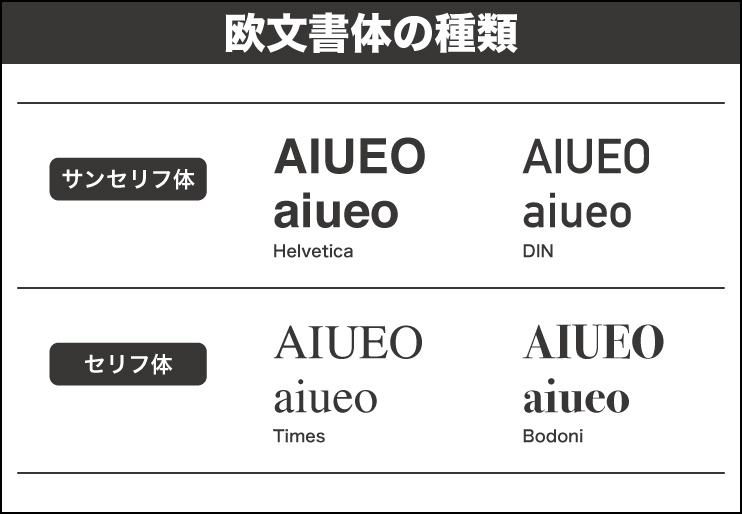
同じ文字でも書体により特徴が異なり見た目のデザインが変わります。大きな分類であるゴシック体と明朝体、サンセリフ体とセリフ体の違いを覚えておくと良いでしょう。
書体が与える文字のイメージとは何か?
デザインが読み手に与えるイメージは、どの種類の書体を使用するかによって大きく変わります。実際に下図2つのデザインを見てみましょう。
左側ではゴシック体とサンセリフ体を使用しています。右側では明朝体とセリフ体を使用しています。デザインレイアウトは同じですが、左側からはポップな感じのイメージを感じます。右側からは少し高級感のあるイメージを感じると思います。
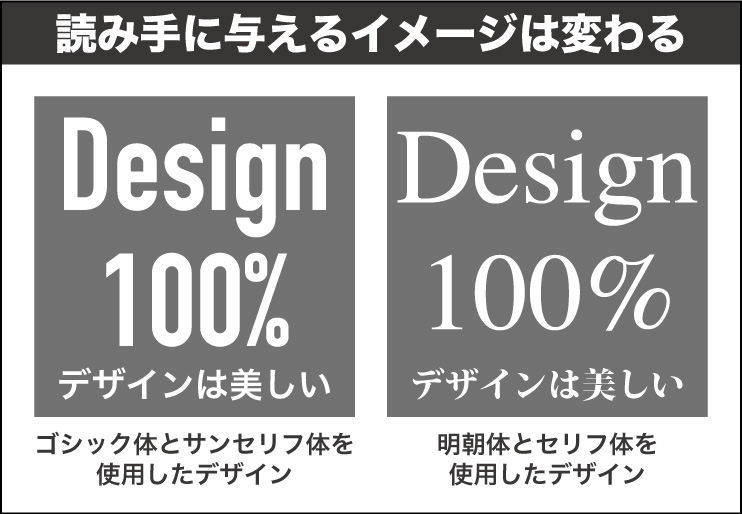
同じデザインレイアウトを使用していても、書体が書体が異なると見た目のイメージが異なります。書体はそれだけデザインのイメージを左右してしまうのです。
文字を書体の持つ力でデザインやレイアウトに生かしていこう!
下図にいくつかの具体的な制作を行ってみました。それぞれを見ると瞬時にイメージが異なることに気がつくと思います。
これは書体本来がもっている力ということです。デザイン初心者は同じデザインであっても基本となる書体を変更して2種類制作を行い、それぞれを見比べるとより効果がわかることだと思います。
自分なりのデザインの概念があるとは思いますが、ここではあえて固定概念を置いて試すと良いでしょう。きっと文字と書体のデザインヒントになることだと感じます。また、自分で何度も試すことで書体の基本知識は自然と身につくことでしょう。
左側はゴシック体を使用し、右側は明朝体を使用しています。
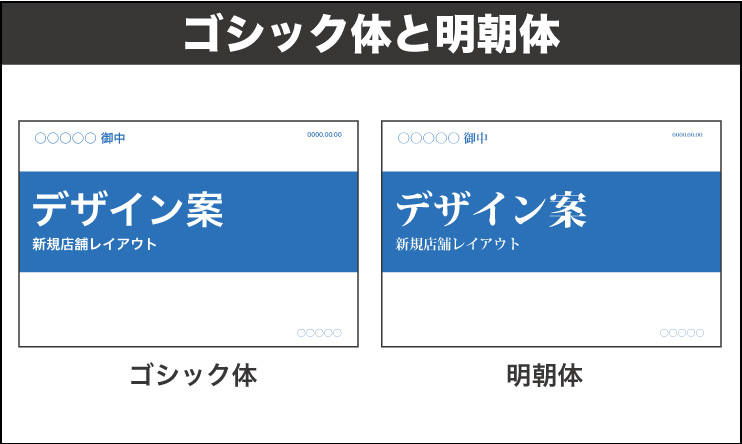
左側はゴシック体を使用することで文字の線幅がほぼ均一であるため視認性が高く、安定感のあるイメージになります。
右側は明朝体を使用することで文字の線幅に強弱があるため左側ゴシック体と比べ、タイトル文字が若干弱く見えますが、厳格・堅い・美しいといったイメージがあります。
下図の左側はサンセリフ体をメインに、ゴシック系の書体でデザインをしています。右側はセリフ体をメインに、明朝体の書体でデザインしています。
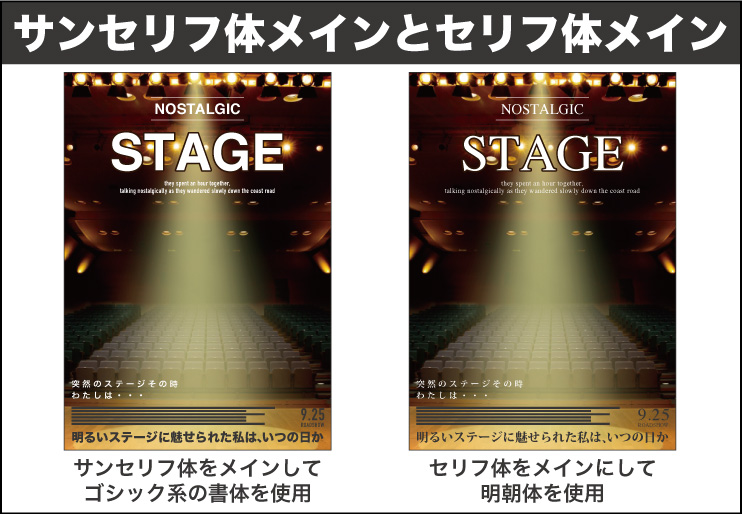
左側はサンセリフ体を使用することでポップな印象はありませんが、ステージやショーなどのエンターテイメント性が感じられます。
右側はセリフ体をメインに使用することで、落ち着いたイメージが強調され、ミステリアスな雰囲気が感じられます。
下図の左側は文章をゴシック体でデザインレイアウトした例です。右側は文章を明朝体でデザインレイアウトした例です。
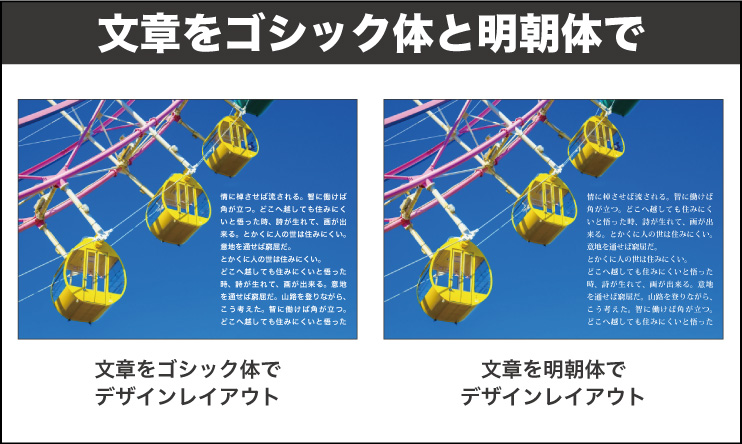
左側は文章をゴシック体でデザインレイアウトすることで楽しそうで、若々しく、ポップなイメージが感じられます。
右側は文章を明朝体でデザインレイアウトすることでゴシック体に比べ、かしこまった印象があり、ノスタルジックな印象も感じられます。
文字には書体という大きな分類があり分類ごとの基本的な特徴とは!?
デザインをする際は書体の種類を覚えることが使いこなすポイントです。
和文の明朝体や、欧文のセリフ体の書体は主に「権威的」「歴史的」「品格」といったイメージを読み手に与えます。これらのイメージは書体の線幅により使い分けると良いでしょう。
明朝体とセリフ体の特徴とは?
明朝体とセリフ体は、文字の右端に「セリフ(うろこ)」と呼ばれる盛り上がった飾りがあります。
また文字中の横線よりも縦線のほうが太い書体の総称になります。この特徴から明朝体とセリフ体は基本的にスマートと見えるため、小さくても視認性や可読性に優れています。
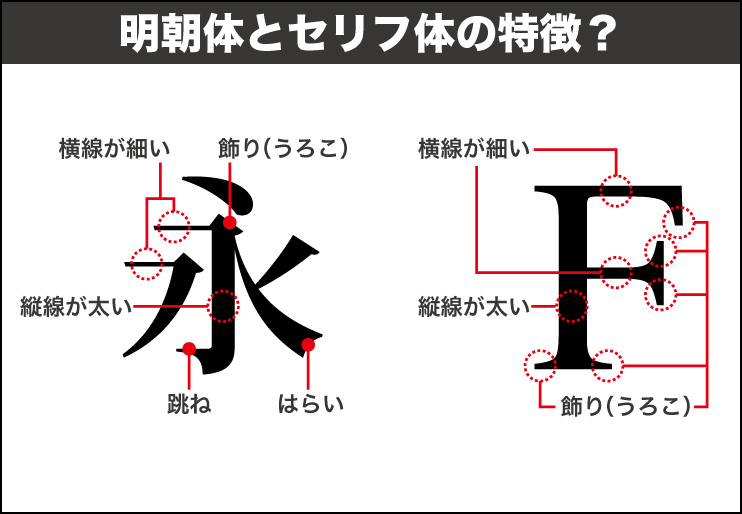
身近な紙面としては、新聞や教科書などの長文で広く使用されています。
明朝体とセリフ体が読み手に与えるイメージとは?
明朝体やセリフ体が読み手に与えるイメージは、縦線の太さによって変わります。
縦線幅が太い書体は「力強い」、「権威的」、「歴史的」、「男性的」、「大人」などのイメージを感じます。
縦線が細くなるにしたがって「弱い」、「柔軟」、「モダン」、「女性的」、「中性的」、「品格」といったイメージを感じることができます。参考例として下図を見てみましょう。
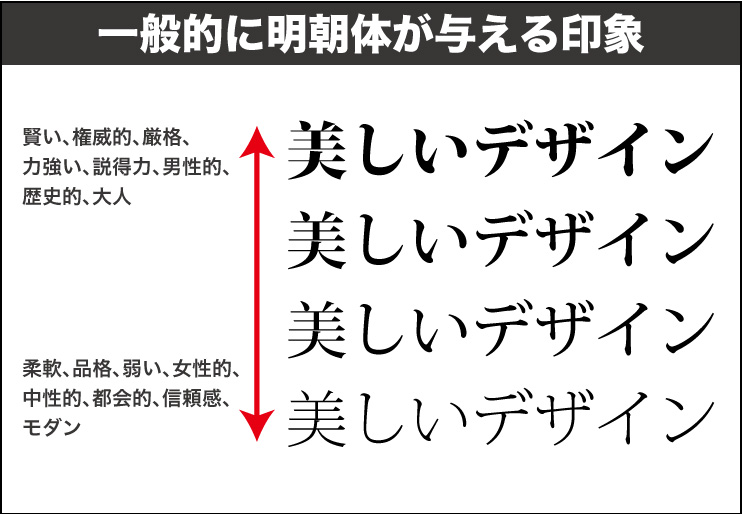
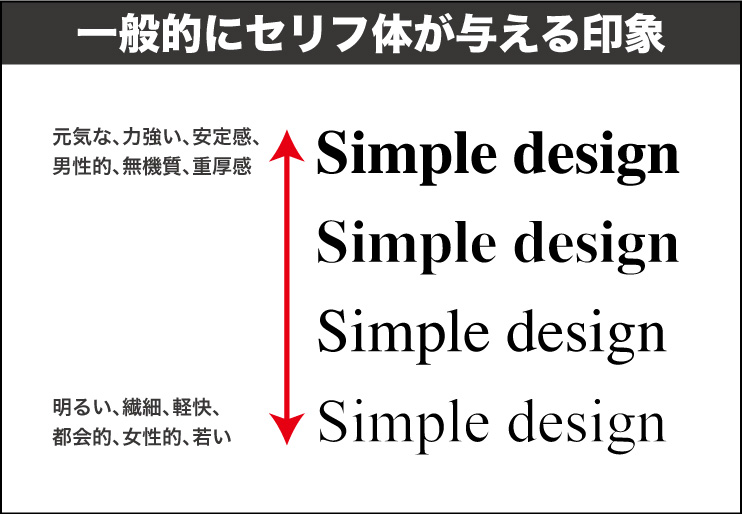
明朝体やセリフ体の太さを選定することはイメージを左右します。
明朝体は手書きした筆文字の楷書を一定のルールで形式化した書体と考えて良いでしょう。
1文字1文字の跳ねやはらいがあるのが特徴です。
セリフ体は手書きの平筆で書かれた文字を一定のルールで形式化した書体です。筆先の跡の飾り(セリフ)が書き始めと終わりにあるのが特徴です。手書きメインのデザイナーさんやキャリアが何十年と長い方は、別名でローマン体と表現する場合もあります。
1つ1つの書体には制作された意図がある。
書体を選定する際は、その書体が開発された経緯なども調べてみると面白い、なるほど!と言った印象に残るものとなります。印象に残れば書体の利用シーンもイメージしやすくなるのではないかと思います。
例えば、デザイナーに人気の「DIN」という書体は元々ドイツ工業規格のために開発された書体です。
その幾何学的な書体のフォルムに目をつけたデザイナーが本来の目的や用途とは異なる、さまざまなデザインで使用したため注目度が高まり、今ではデザインするうえで王道な書体といってよいほどの存在になりました。
ゴシック体とサンセリフ体の特徴とは?
ゴシック体とサンセリフ体は、明朝体とセリフ体にあるセリフ(うろこ)がなく、文字の縦横線が均一の太さになっている書体の総称になります。
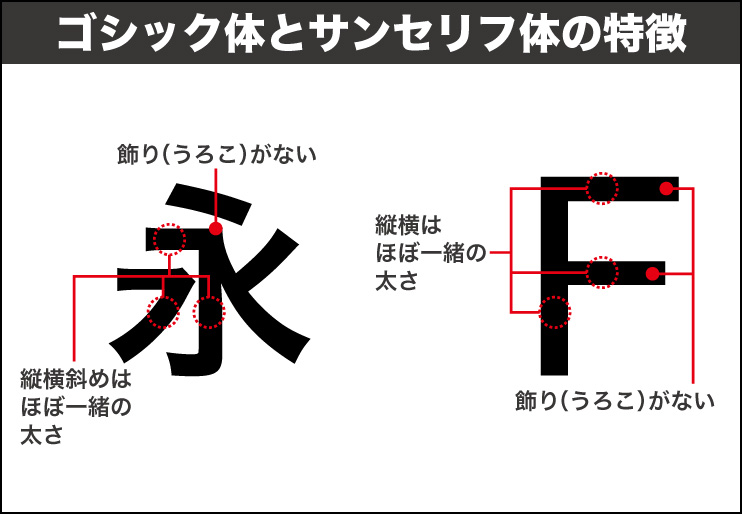
塗りの面積が大きい特徴から「黒く目立つ」ように見えるため、小さくても高い視認性を確保できます。強調したいタイトルや見出しなど、さまざまなグラフィックやWebデザインはもとより、公共施設のサインなどでも幅広く使用されています。
ゴシック体とサンセリフ体が与えるイメージとは?
ゴシック体やサンセリフ体が読み手に与えるイメージは、文字線の太さにより変わります。
線幅が太い書体は「力強い」「元気な」「男性的」「厳格」「安定感」などのイメージを感じます。
線幅が細くなるにしたがって「明るい」「繊細」「女性的」「中性的」「都会的」といったイメージを感じることができます。参考例として下図を見てみましょう。
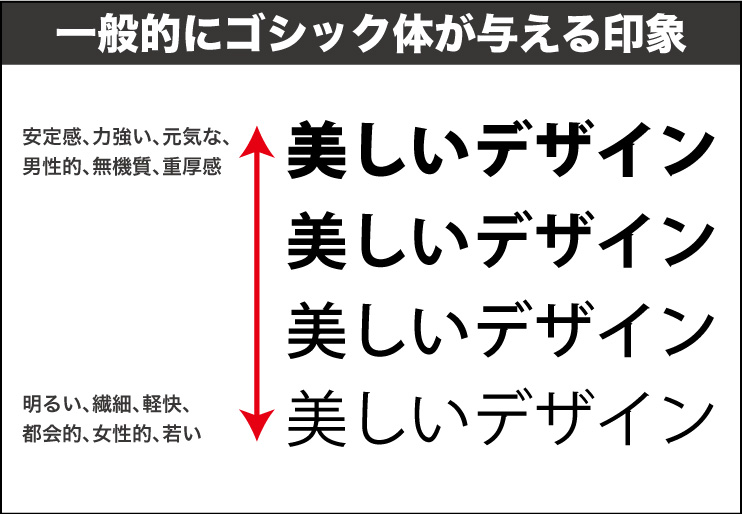
ゴシック体やサンセリフ体の太さを選定することはイメージを左右します。
ゴシック体とサンセリフ体は、縦横の線幅がほぼ同じです。余分な装飾がなく現代的なイメージの書体です。視認性を強く確保できます。
文字の形状を表す用語に「書体」と「フォント」の2種類がある!?
細かい内容になりますが、書体とは字体を統一したコンセプトに基づいてデザインされた形状のことです。
和文には明朝体、ゴシック体などがあります。ではフォントとは何かと言いますと元々は金属を使う活字印刷時代に同じサイズ、同じデザインの欧文活字を指した言葉なのです。(当時は文字サイズが違うだけでも別名称だったとか聞いたことがあります)。
現在では共通デザインのひと揃いの文字の集まりのことを「フォント」と呼ぶことが多いです。書体とフォントはほぼ同じ意味合いとして使われることも多く使用される用語は、あいまいになっているのが実情です。
デザイン初心者が覚えておくべき文字と書体基本知識のまとめ
- 和文はゴシックと明朝体、欧文はサンセリフ体とセリフ体があり基本書体として覚える。
- 書体のイメージを覚えてシーンにあった書体選びをする。
- 1つ1つの書体には誕生秘話があり、それを知ることで書体のイメージを覚えることができる。
- 現代のデザインで使われる用語として書体とフォントは同類語として使われている。
- デザインに書体を使うときには候補を絞り2〜3種類に減らすこと。
- デザイン初心者はファミリー書体を使うことで統一感を演出すると良い。
私もデザイン初心者の頃は文字を様々な書体で表現し感動していました。
デザインであれこれと使用した結果「その書体ではない方が良い」や「文章自体を削除する修正」等を経験したことがあります。
これは今思えば、思いつきで書体を選び制作物の目的や用途のデザインに即していない結果であったことは間違いありません。
書体選びはデザイン要素である色や写真、揃える箇所は揃える、グループ化する等様々な要素の1つです。要素の1つですが、文字を読ませるという情報伝達は書体選びにかかっているといっても過言ではありません。
デザイン初心者のうちは書体選びは難しいかもしれませんが、この記事を読んで少しでも知識として取り入れることができればデザインをワンランク上まで上達させる要素の1つになるのではないかと思います。